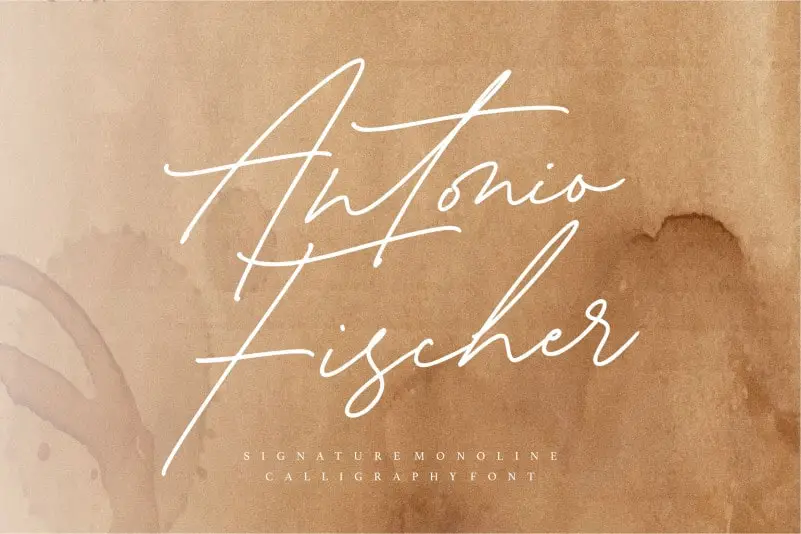
Antonio Fischer Signature Monoline Font – Download Grátis
A ‘Antonio Fischer Signature Monoline Font’ é uma elegante escolha para qualquer projeto que busque um toque único e sofisticado nas suas criações visuais. Seja para projetos de embalagem de produtos, trabalhos de marca ou até mesmo editoriais em revistas, ela oferece uma presença assertiva que complementa os elementos do design sem tirar o foco da sua mensagem central. Além disso, seu uso em redes sociais e para expressar mensagens acima de fundos adiciona um toque atraente que pode dar ao texto um caráter imediato e memorável. Esta fonte é especialmente perfeita para eventos especiais como casamentos, onde desejas transmitir uma atmosfera única ou simplesmente desejas criar um estilo único em seu trabalho. Seja ele o uso de letras maiores ou menores, a ‘Antonio Fischer Signature Monoline Font’ consegue manter sua essência sem perder o equilíbrio e a proporção necessários para qualquer tipo de projeto gráfico. Através do seu design monolinéico minimalista mas poderoso, você pode expressar sua personalidade através da escrita. Sem dúvida, é uma fonte que se destaca em um mundo de opções variadas e permite ao criador expressar a essência e o sentimento do projeto de maneira única.